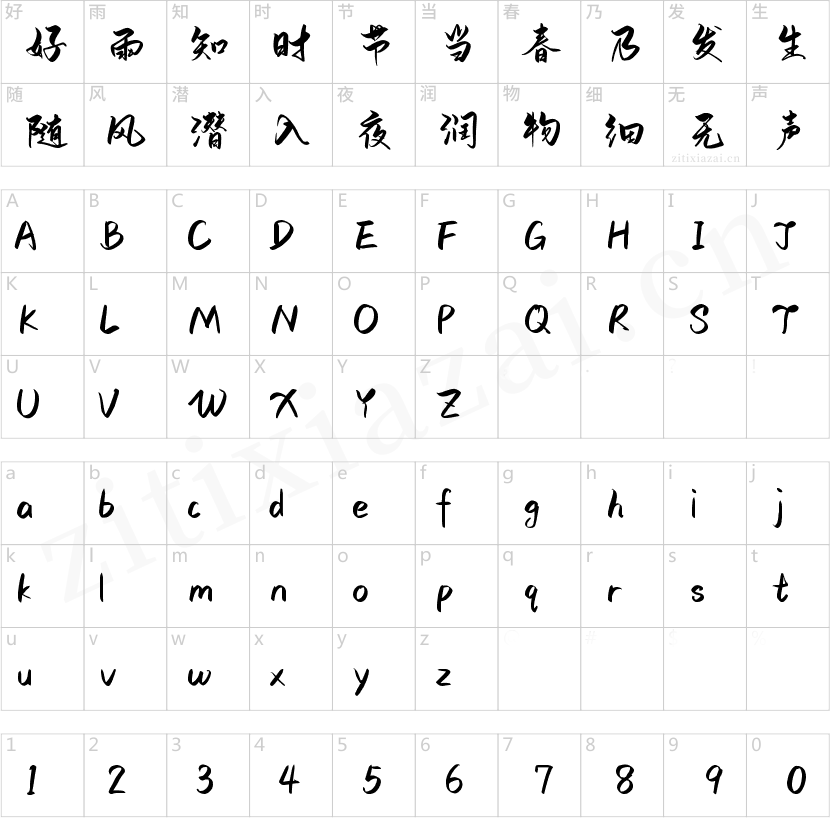
Aa无事小神仙
Aa无事小神仙字体
Aa无事小神仙是一款非常具有艺术性的字体,它的设计灵感来源于对古典艺术的研究,同时又融入了现代字体设计的元素。字形优美,笔画粗细变化自然,给人以大气、典雅的感觉。Aa无事小神仙是一款既传统又现代的字体,它的设计充满艺术感,美观大方,实用性也非常强。无论是对于设计师还是对于普通读者来说,都是一种非常不错的字体选择。Aa无事小神仙适合用于具有艺术感的场合,比如海报、宣传单张、书籍封面等。由于其字形流畅且具有动态感,也适合用于大量的文本排版,如报纸、杂志等。